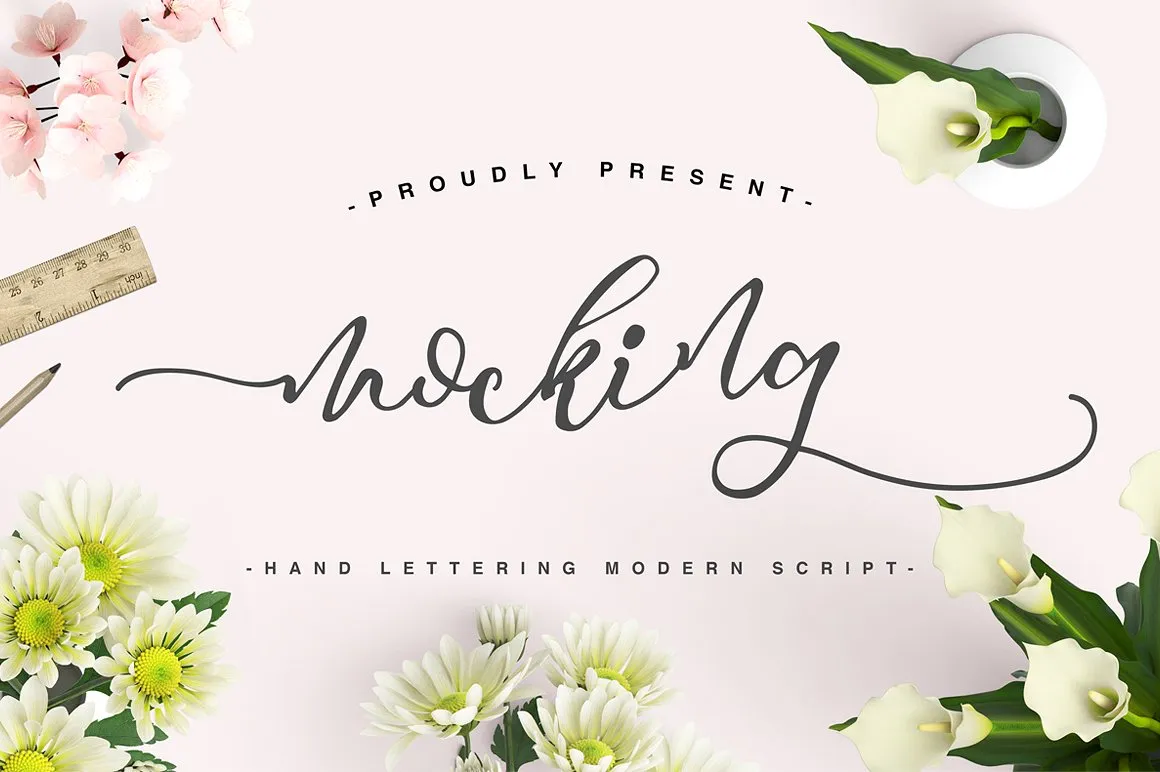
Descubra a encantadora Mocking Script Font! Este script elegante e flerteiro é perfeito para uma variedade de projetos. Desenvolvida pela Awakening Studios, Mocking Script é ideal tanto para criações digitais quanto físicas. Perfeita para branding, cartões de convite de casamento ou até mesmo cartas personalizadas, esta fonte também atende a demanda romântica e feminina. A sua estética encantadora torna-a um recurso visual maravilhoso para aplicativos de marcação, cabeçalhos de blogs e design editorial. Com seus finos caracteres finais decorativos e linha base que “chuta” para cima, a Mocking Script ganha uma sensação especial. Esta é fonte perfeita para criar cartões de cumprimentos, convites de casamento ou mesmo logotipos românticos e femininos. Se você está procurando por um estilo elegante e delicado que enriqueça suas criações digitais, esta font é definitivamente algo a ser considerado. Descubra o encanto da Mocking Script hoje em seu download gratuito!